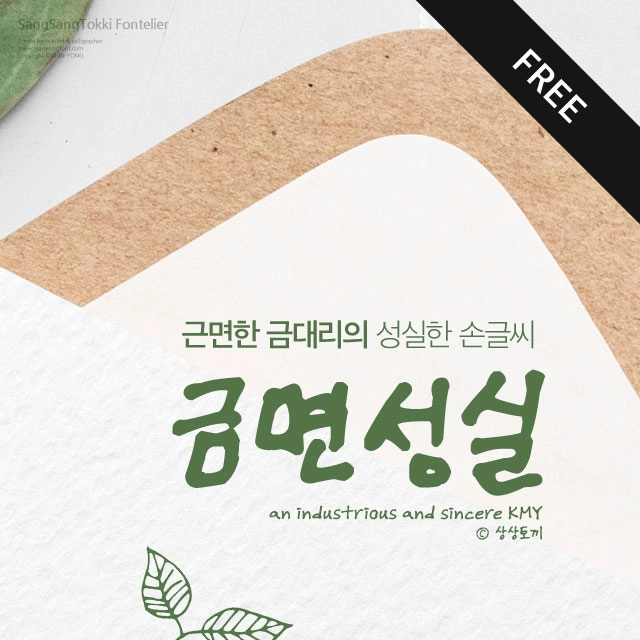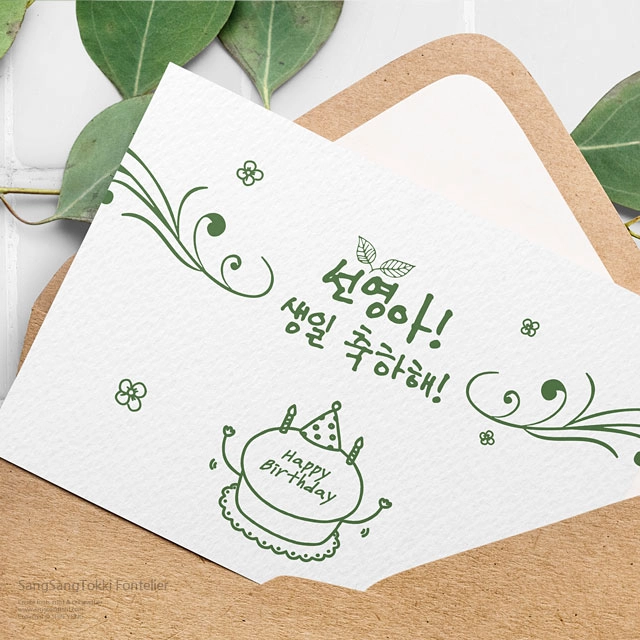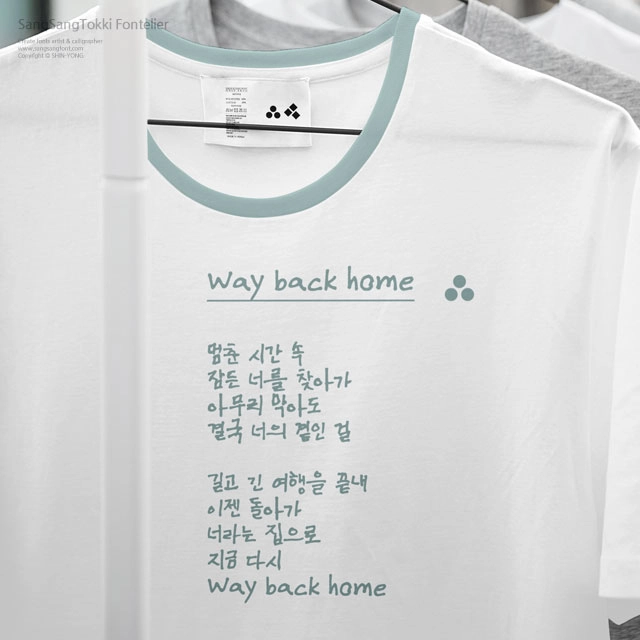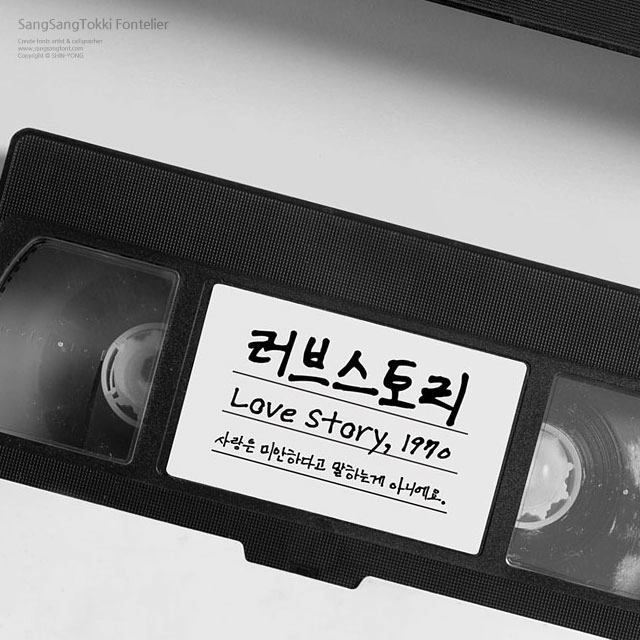
금면성실
근면한 금대리의 성실한 손글씨, 금면성실!
요령 부리지 않고, 맡은바 책임을 다하는 금대리의 성실한 손글씨 <금면성실>은 상상토끼 용이 작가의 대한민국 1인1폰트 세번째 주인공인 금대리님의 손글씨를 기초로 해서 만들어진 폰트입니다. 소중한 글씨로 멋진 폰트를 만들게 허락해준 금대리님께 감사의 마음을 전합니다. |